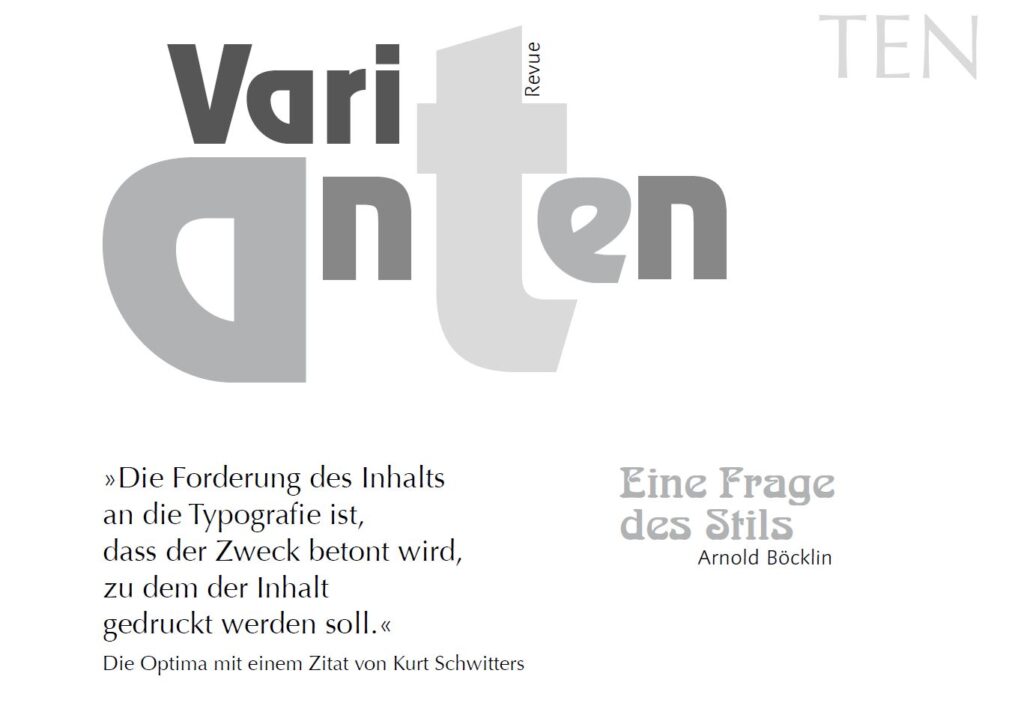
Antiqua-Varianten
Diese Gruppe umfasst Schriften, die zwar an die Antiqua anknüpfen, sich aber keiner der klassischen Klassen zuordnen lassen. Häufig handelt es sich um dekorative Entwürfe, die als Display- oder Auszeichnungsschriften genutzt werden. Hierzu gehören etwa Jugendstil-Schriften wie Arnold Böcklin oder Eckmann, aber auch moderne Mischformen wie Optima (Hermann Zapf) oder Rotis (Otl Aicher).
• Merkmale: nicht eindeutig den Antiqua-Klassen 1–6 zuordenbar, oft experimentell oder dekorativ.
• Beispiele: Arnold Böcklin, Rotis Semi Serif, Mambo Bold, Broadway, Revue, Blur, Eckmann.